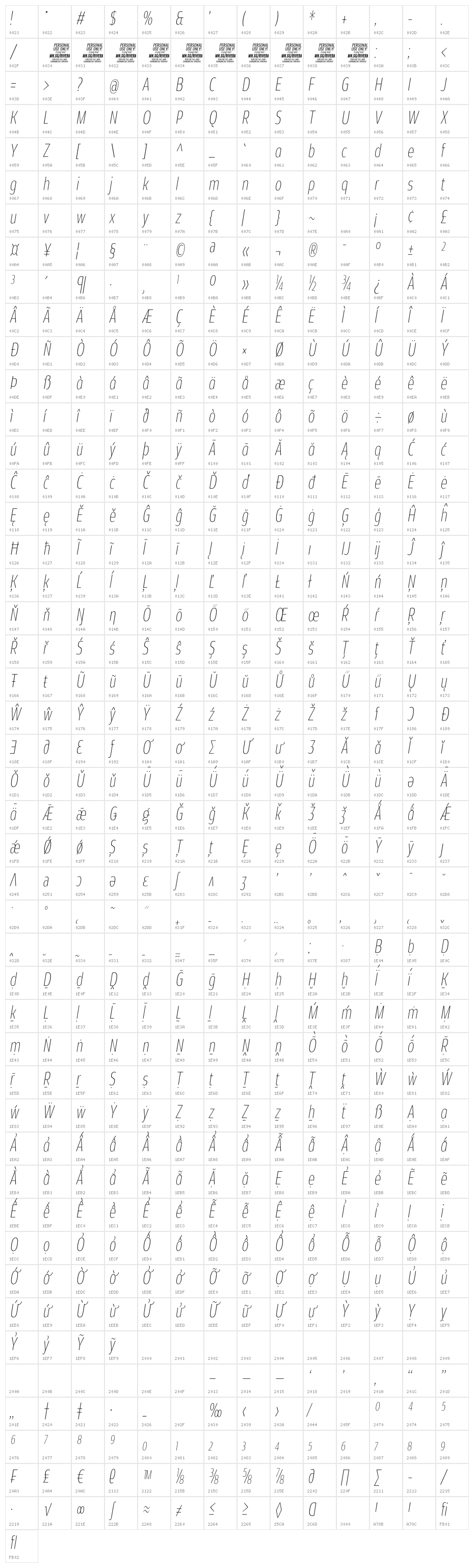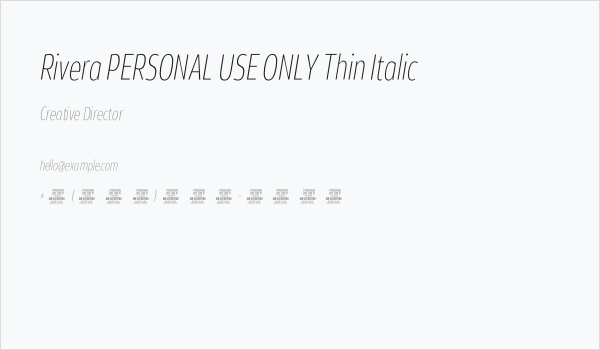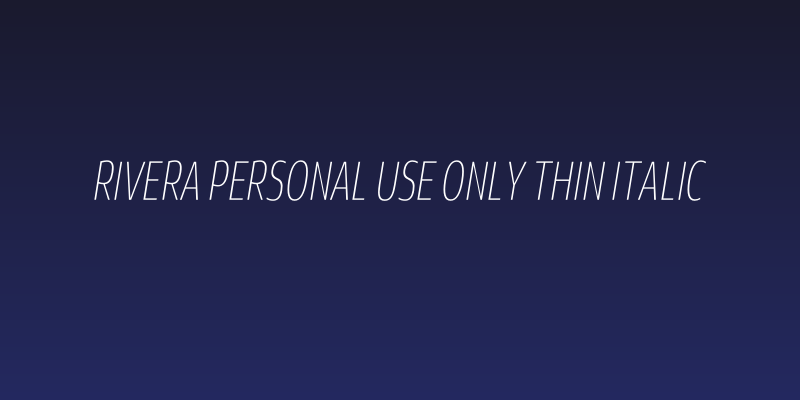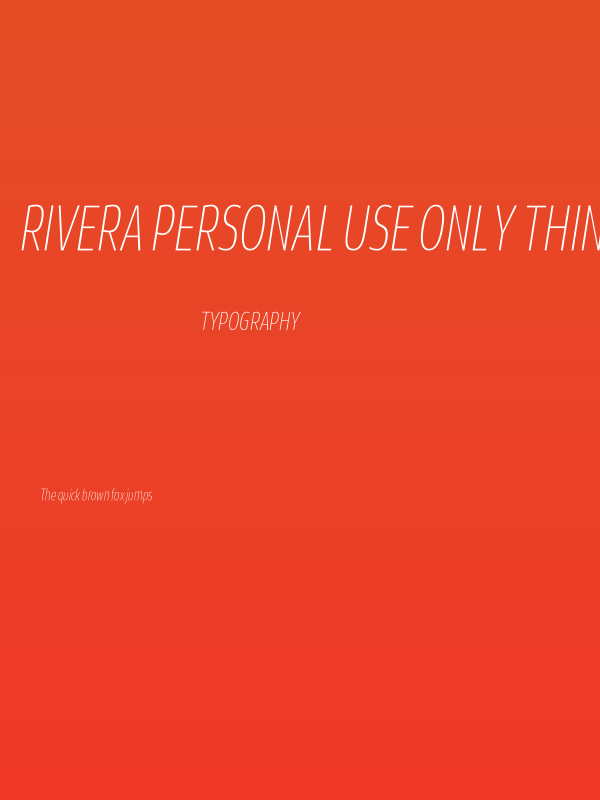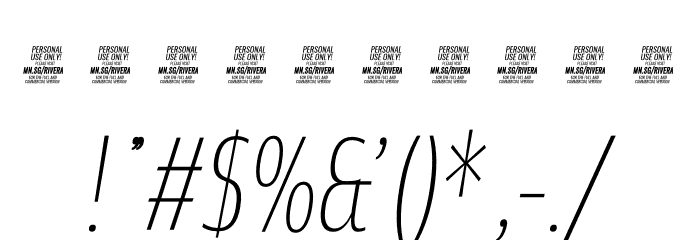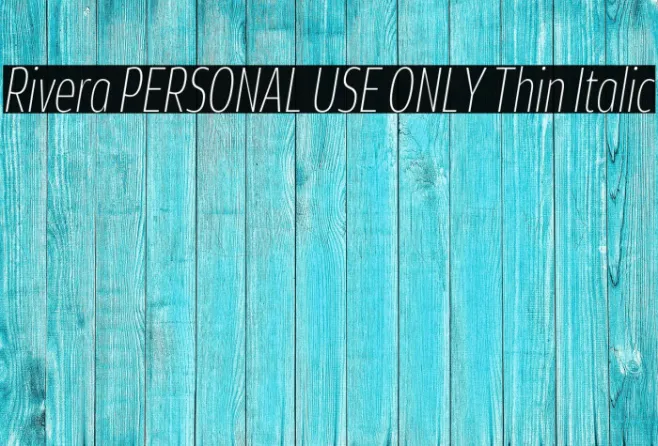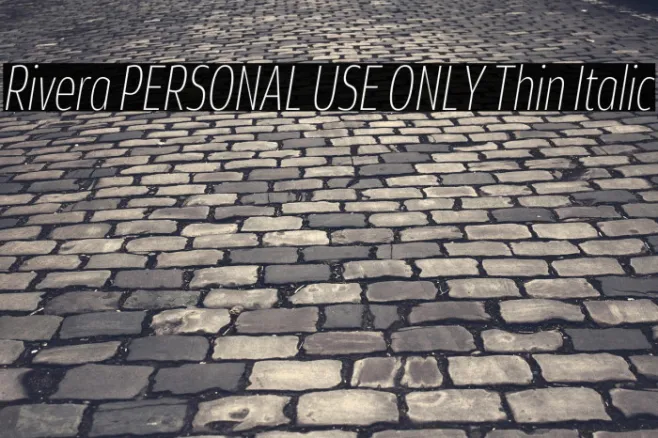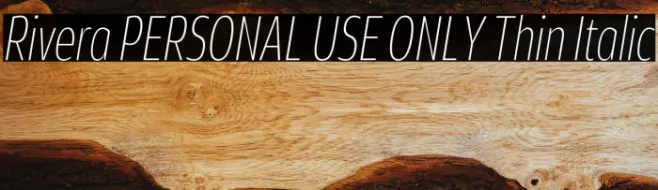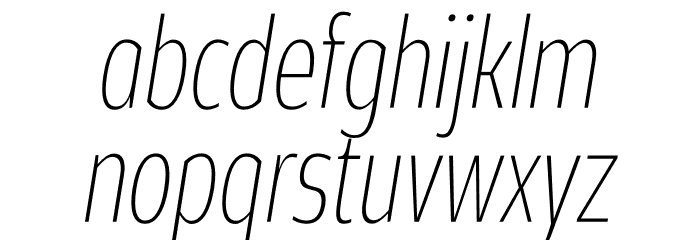
Rivera PERSONAL USE ONLY Thin Italic Font
| Projets proposés | Ideal for fashion magazines, luxury branding, elegant invitations, and modern website headers. |